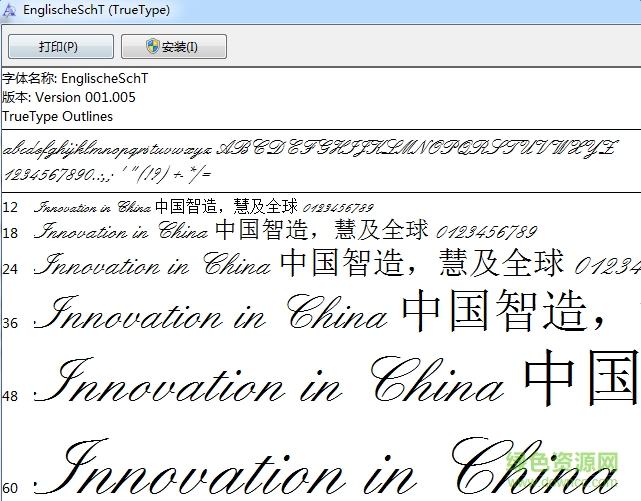
englischescht字體是一款應(yīng)用個(gè)設(shè)計(jì)行業(yè)的英文個(gè)性字體,該字體可以廣泛應(yīng)用于廣告設(shè)計(jì)、宣傳海報(bào)、ppt、影視制作以及任何使用文字的領(lǐng)域,有需要的朋友可以免費(fèi)下載收藏。
englischescht字體是一款英文字體庫中的個(gè)性字體,該字體的形體飄逸,顯得比較秀氣,有需要的朋友可以來綠色資源網(wǎng)下載使用!